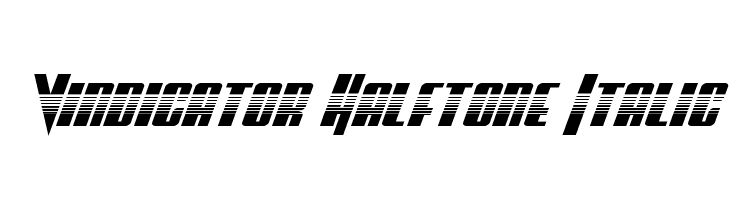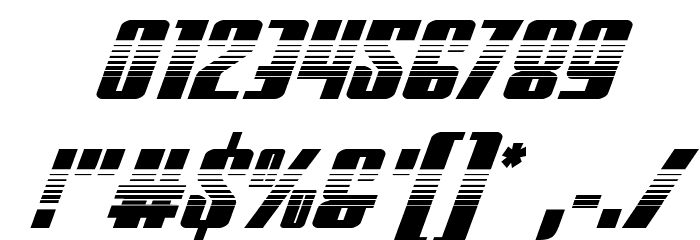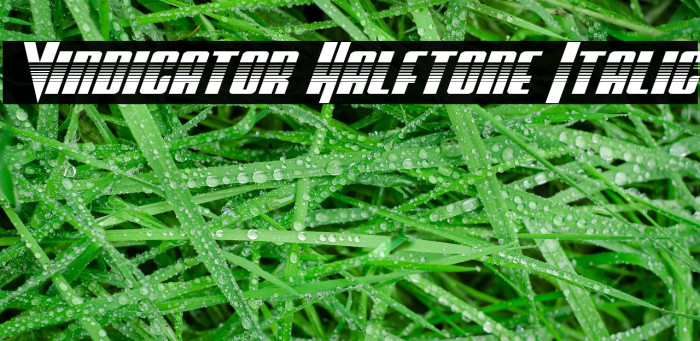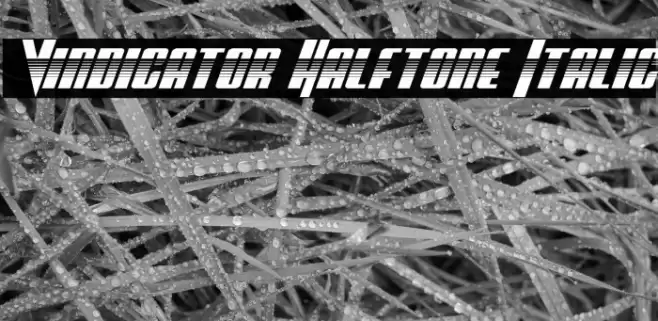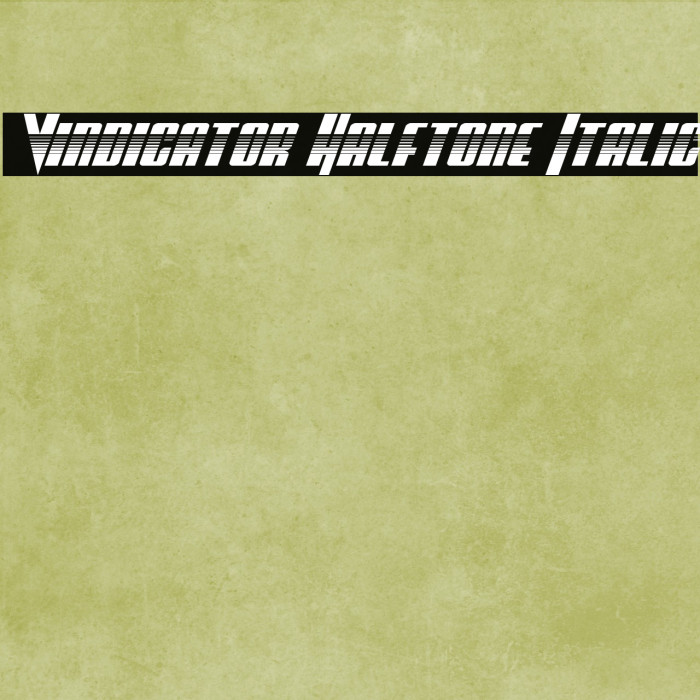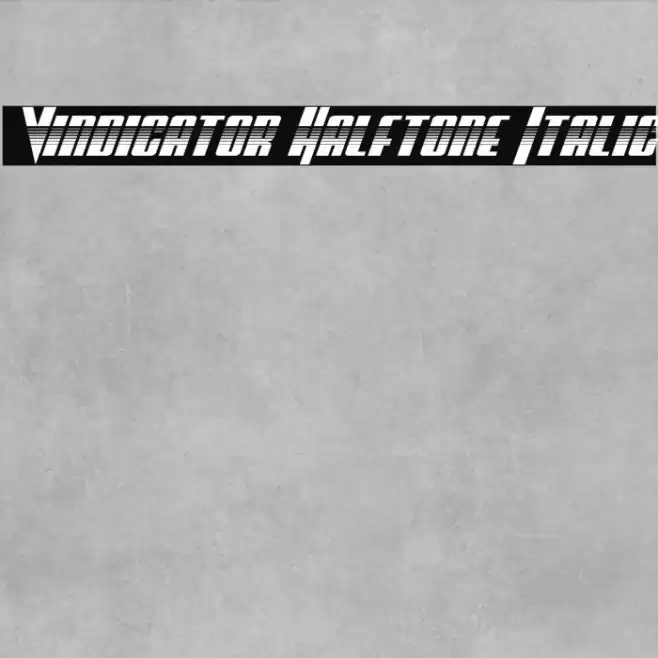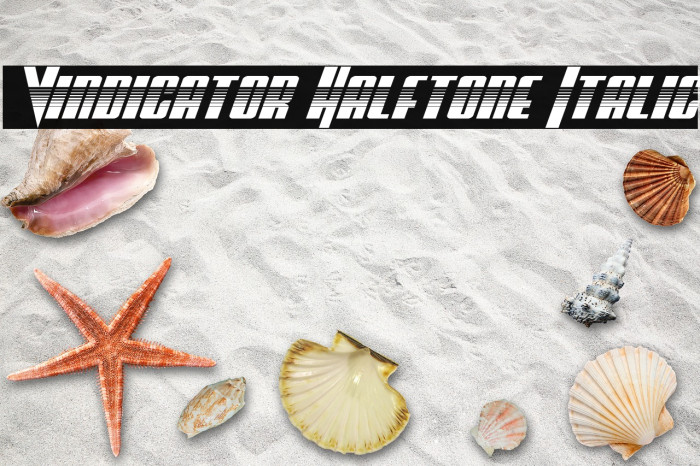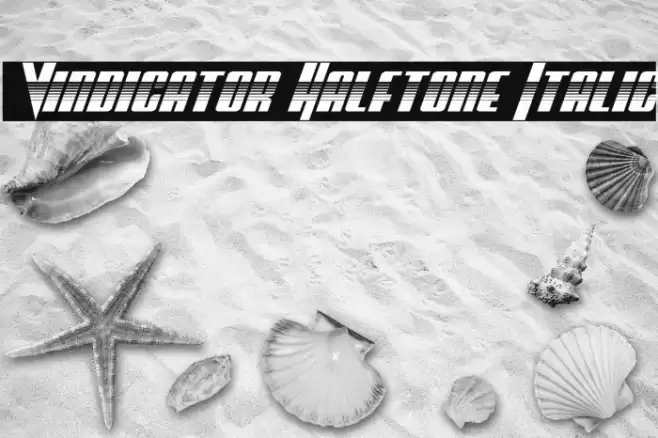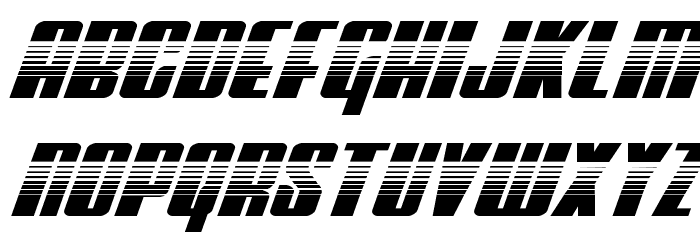
Vindicator Halftone Italic Font
✎ Thick
| श्रेणियाँ | Thick |
| इटैलिक | Yes |
| उपयोग का मामला | Headlines, Logos |
| सुझाए गए प्रोजेक्ट | Ideal for posters, logos, and headlines that require a bold and modern aesthetic. |